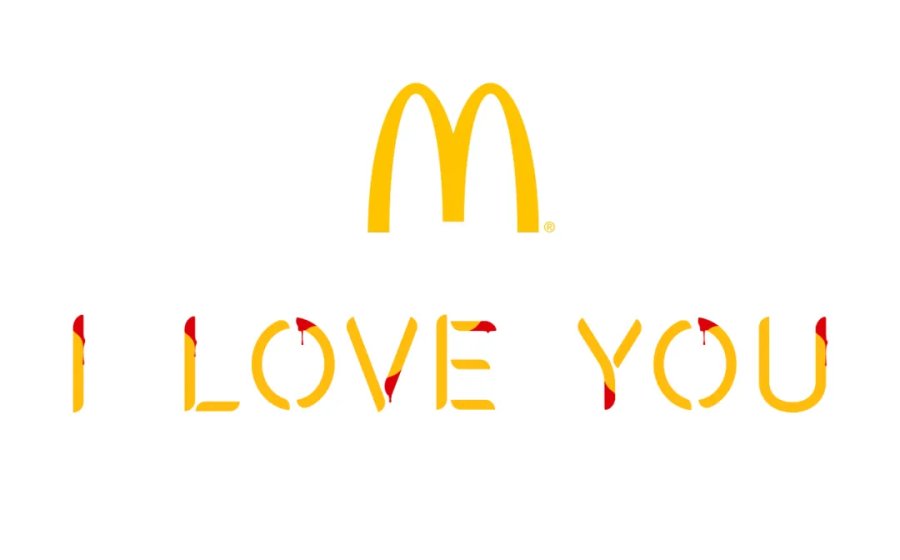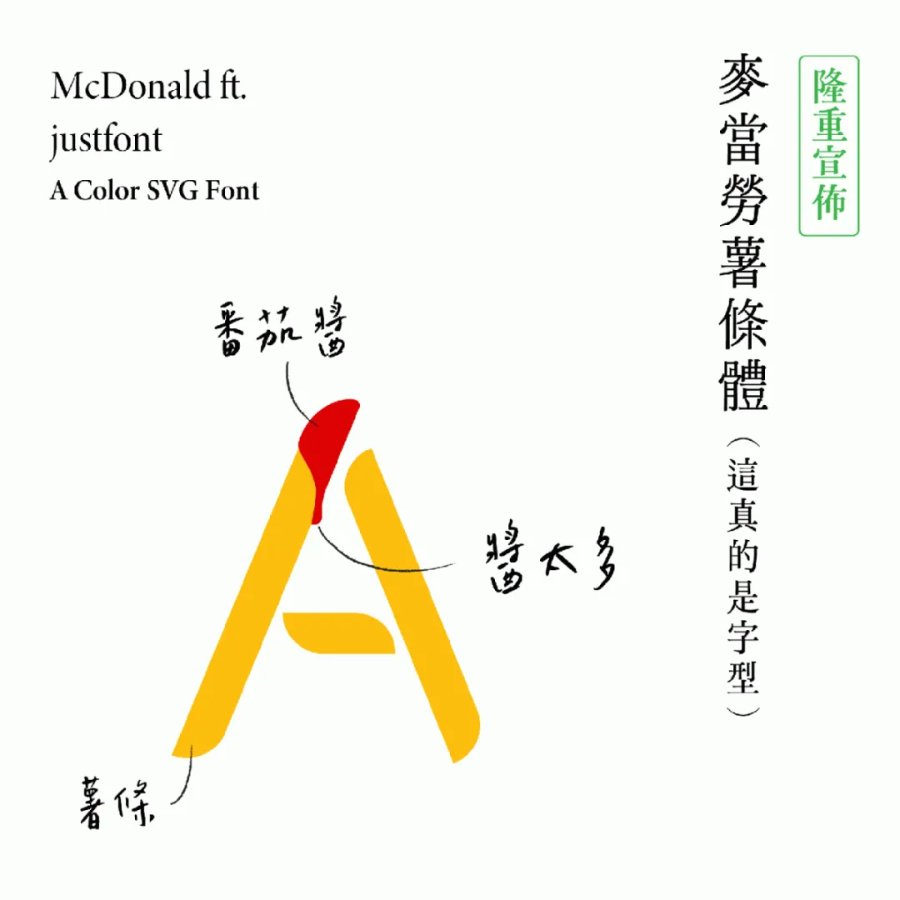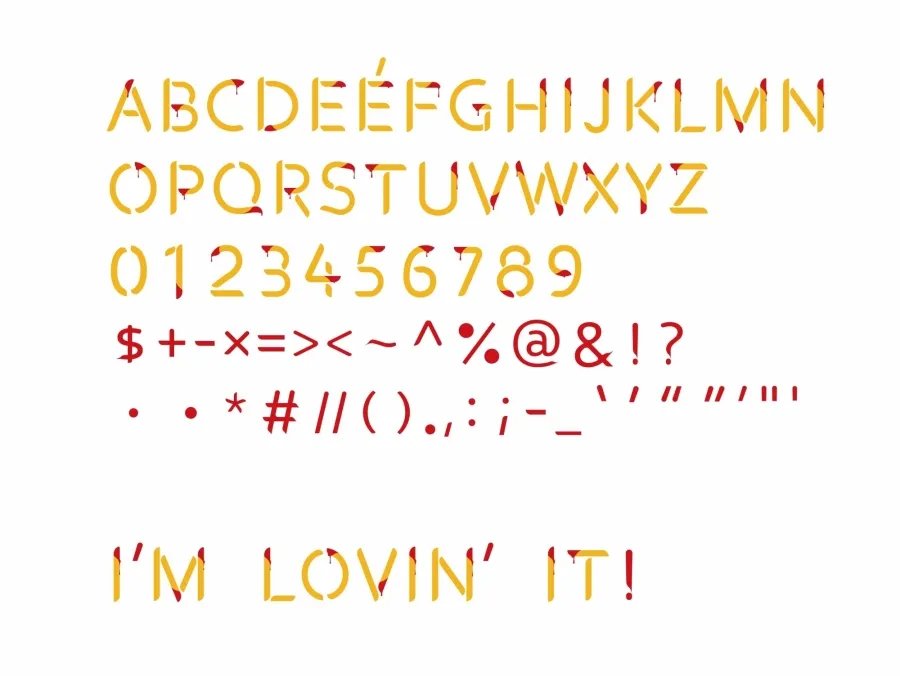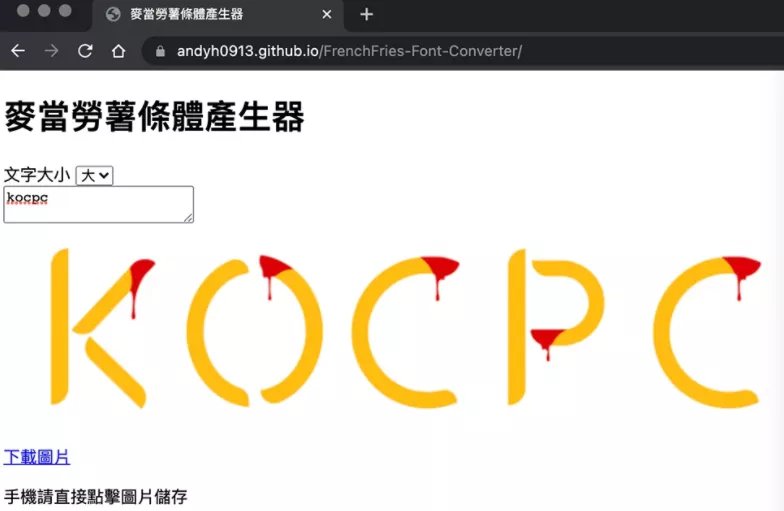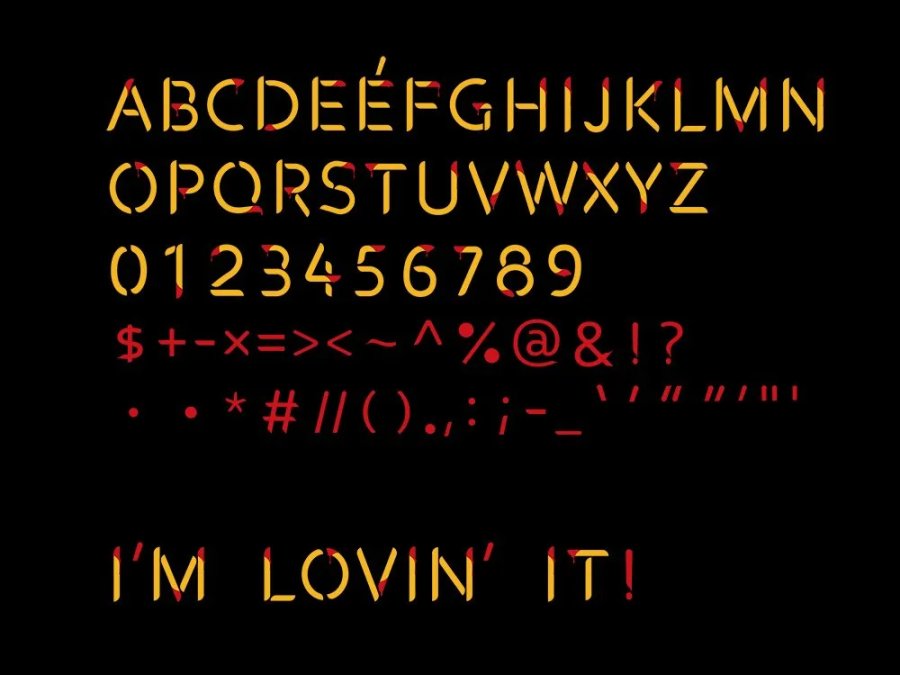
周末就是万圣节了!除了人要装扮,字体也要装扮一下。
麦当劳今推出了万圣节限定薯条字体。
这是继去年麦克鸡块体之后,麦当劳这次以金黄的薯条和必备的番茄酱为灵感,除了开放免费下载也能商业使用!
同时麦当劳也提供薯条体与麦克鸡块体的网页产生器,让所有民众都能透过产生器快速存取麦当劳字体。
去年,麦当劳就推出过过一款鸡块字体,让大家可以使用造型特殊的字体设计各种美术作品。
原标题:麦当劳推出新字体:“薯条体”。可免费商用